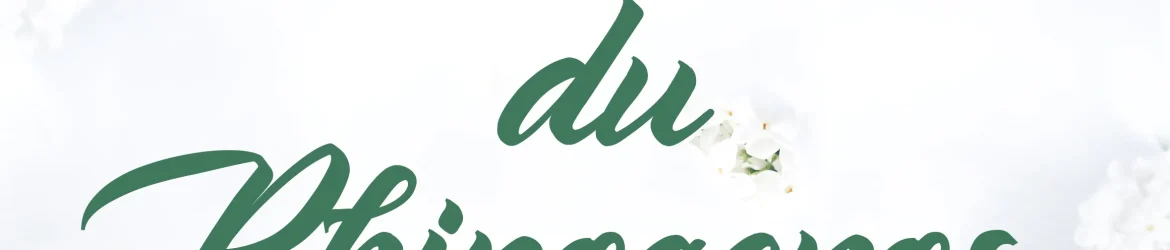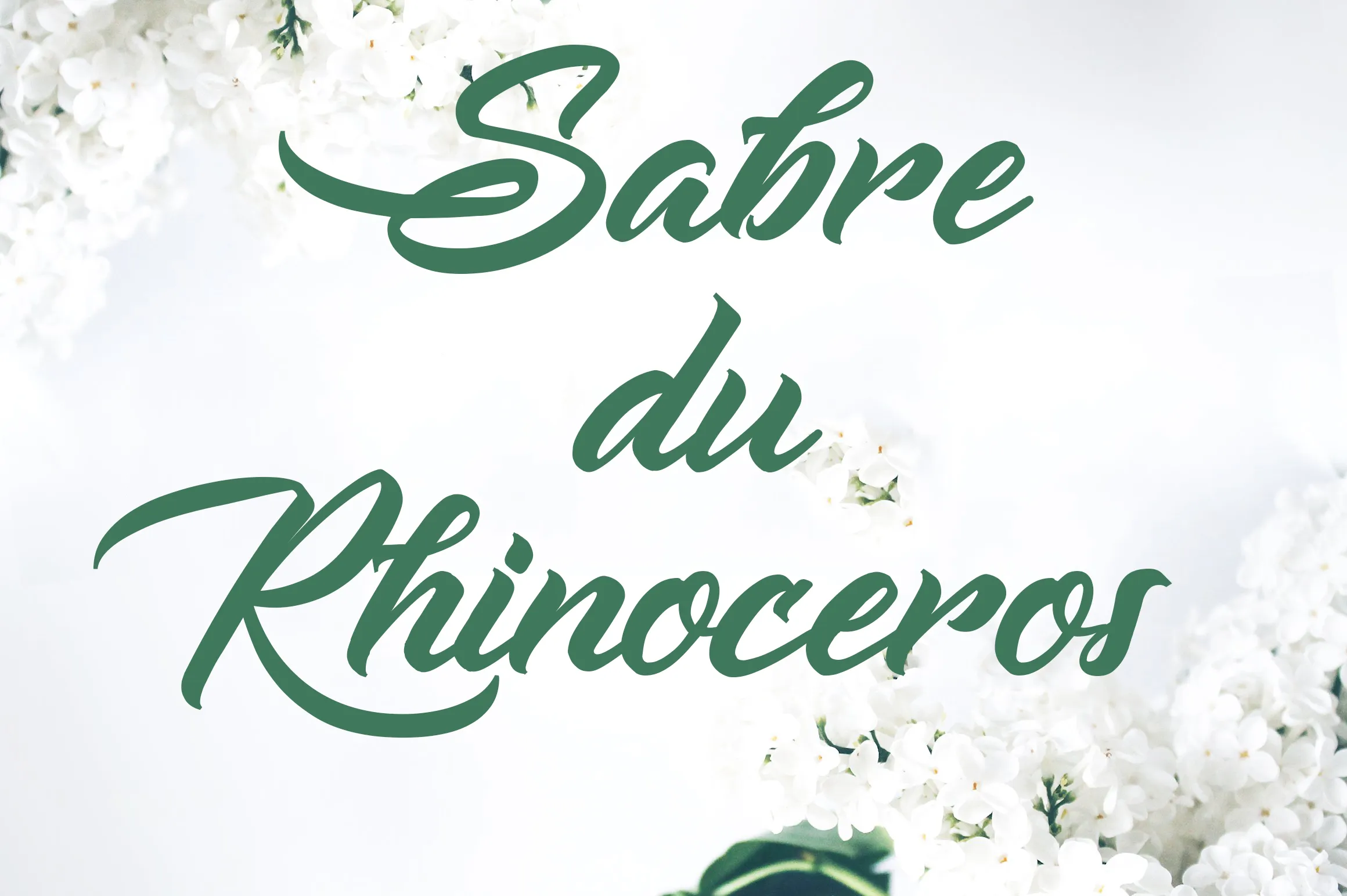
Sabre du Rhinoceros Font
A Sabre du Rhinoceros é uma fonte escrita a mão que transmite autenticidade através de seu estilo de caligrafia única. Suas linhas leves e suaves combinam perfeitamente com projetos variados, como logos, assinaturas, design de embalagens, headlines em blogs e todos os seus trabalhos impressos. Esta fonte é ideal para quem busca um toque distintivo e aconchegante que se destaca nos mais diversos tipos de projeto visual. Seja você uma marca empresarial ou criador de conteúdo, a Sabre du Rhinoceros oferece a perfeita combinação entre modernidade e elegância, tornando-a uma escolha inteligente para qualquer projeto em que o estilo seja crucial. Com seu designer Octotype, esta fonte escrita a mão convida você ao universo deliciosamente elaborado de personalização e design.